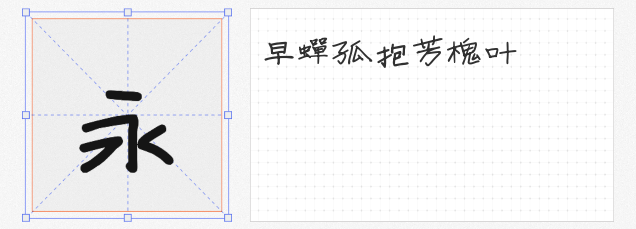
免费商用手写字体推荐:增添设计温度的三款宝藏选择
在追求个性化与设计感的今天,手写字体以其独特的韵味和温度,成为众多设计师心中的宠儿。今天,就为大家推荐三款不仅免费商用,而且在设计中能大放异彩的手写字体——“寒蝉手拙体”、“清松手写体”以及“杨任东竹石体”。它们各自承载着不同的风格与故事,为你的设计作品增添一抹不可复制的魅力。
1. 寒蝉手拙体
“寒蝉手拙体”以其独特的手拙之美脱颖而出,仿佛能听见笔尖与纸张摩擦的细微声响。这款字体精心捕捉并放大了手写时的自然瑕疵,营造出一种极为逼真的手写体验。尽管它的应用范围或许略显局限,但正是这种小众与独特,让它在特定的设计场景下成为无可替代的选择。无论是手写笔记风格的邀请函,还是复古风格的海报设计,“寒蝉手拙体”都能完美融入,传递出手作的温度。
2. 清松手写体
“清松手写体”源自设计师游清松的真实手稿,通过“守写字”网站与现代技术的结合,将这份手写情怀转化为数字字体。三款字体各具特色,既有日常笔记的随性,也不乏正式文件的端庄。它们保留了原子笔书写的流畅与自然,适合用于日记、笔记、信笺或是任何需要温馨、亲切氛围的设计项目中,让人一眼就能感受到书写者的情感与温度。
3. 杨任东竹石体 字体家族
“杨任东竹石体”则是一款功能性与艺术性并重的字体。它不仅严格按照GB2312-80标准书写,还增补了常用汉字,单个字体文件即包含7311个字符,满足99.8%的日常需求。更令人惊叹的是,该套字体拥有7个字重,从纤细到粗犷,总计超过50000个字符,为设计师提供了极大的灵活性与创作空间。无论是简约现代的UI界面,还是充满文化底蕴的书籍封面,“杨任东竹石体”都能以其厚重而不失灵动的笔触,展现出别样的设计语言。
这三款免费商用手写字体,各自以独特的方式诠释着手写的魅力,为你的设计作品增添一抹不可复制的人文情怀。不妨尝试一下,让设计因手写而不同!